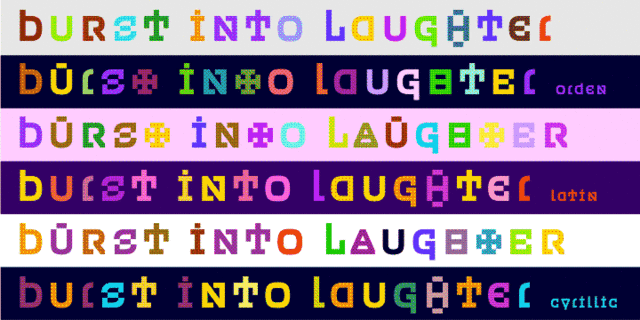
ПТ Орден™ Шрифт выполнен дизайнером Олегом Карпинским в 2000-2001 годах и лицензирован фирмой «ПараТайп». Орден - настоящий кирилловский шрифт. В нем использованы старинные кирилловские графемы d, z, N (с диагональным штрихом), симметричные формы Y ,Ч и Щ, редкие в современной типографике. Другие отличительные особенности: только прописные знаки и минускульные цифры. Вместо строчных в шрифте находятся прописные, за исключением некоторых знаков, представляющих собой альтернативные начертания прописных букв. Годен для применения в рекламе и акциденции.
оригинальный, твердый, самобытный, характерный, грубый, железный, индустриальный, мужественный, загадочный, молодежный, странный, квадратный, ровный, урбанистический, рабочий, экспериментальный, агрессивный